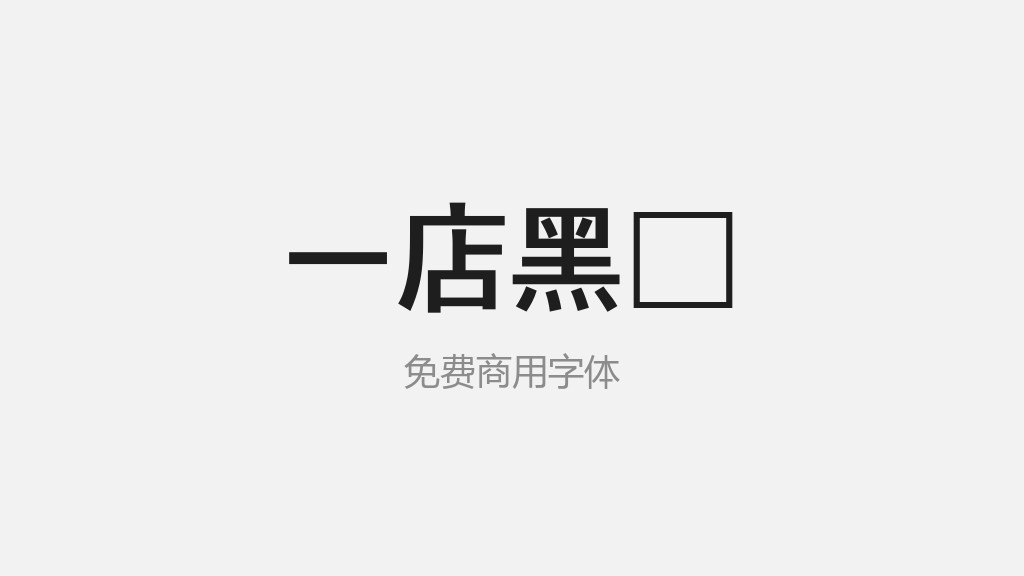
字体介绍
一店黑体(ONE Mobile)是韩国 ONE store 推出的一款针对移动使用而优化的字体,具有现代而舒适的字形设计环境和优化的文本行。字体包含 Light、Regular、Bold 三个字重,适用于移动端界面、海报设计、包装设计等多种场景。
- 字体名称:一店黑体(ONE Mobile)
- 字体作者:一店(韩国 ONE store)
- 字体字重:3个(Light / Regular / Bold)